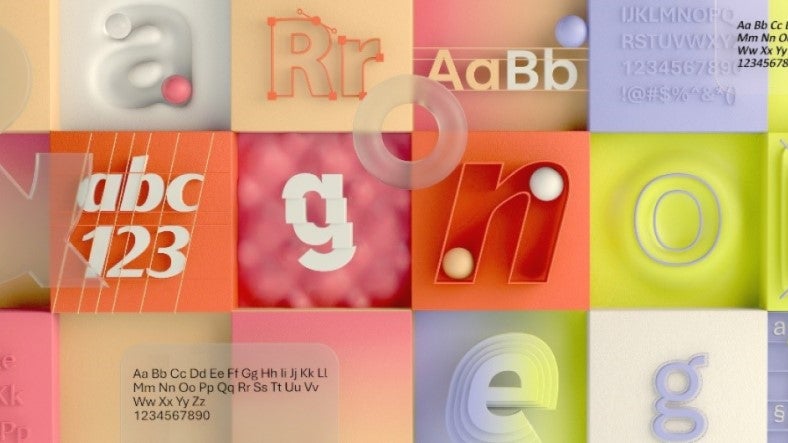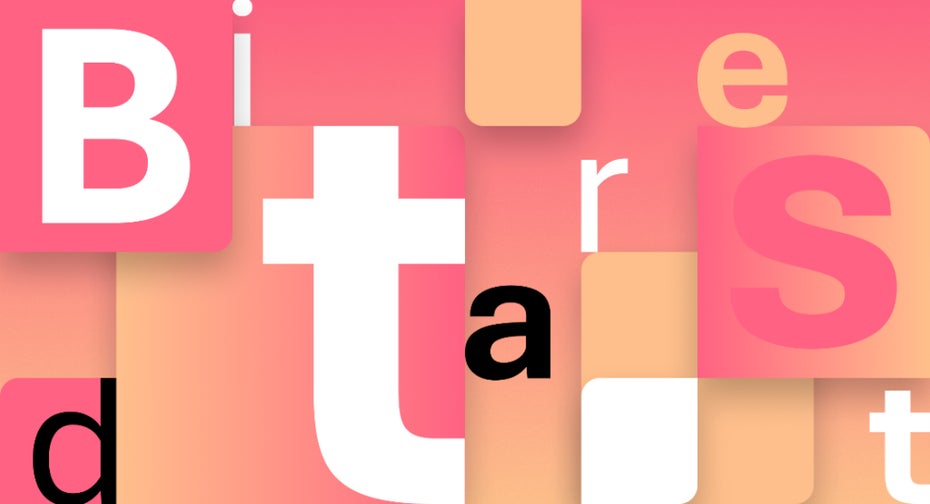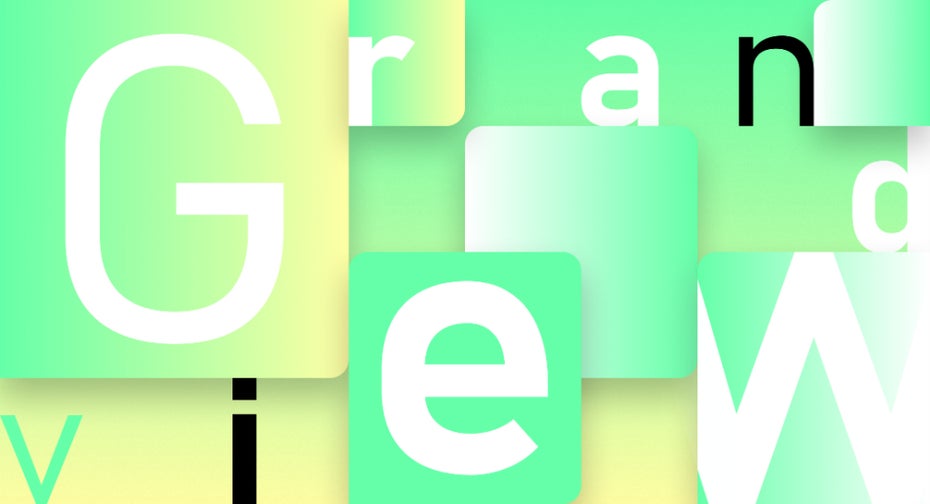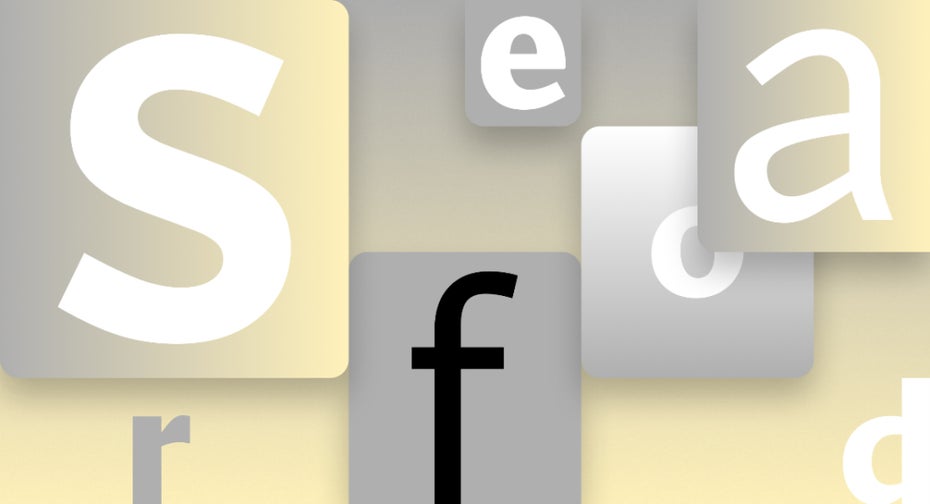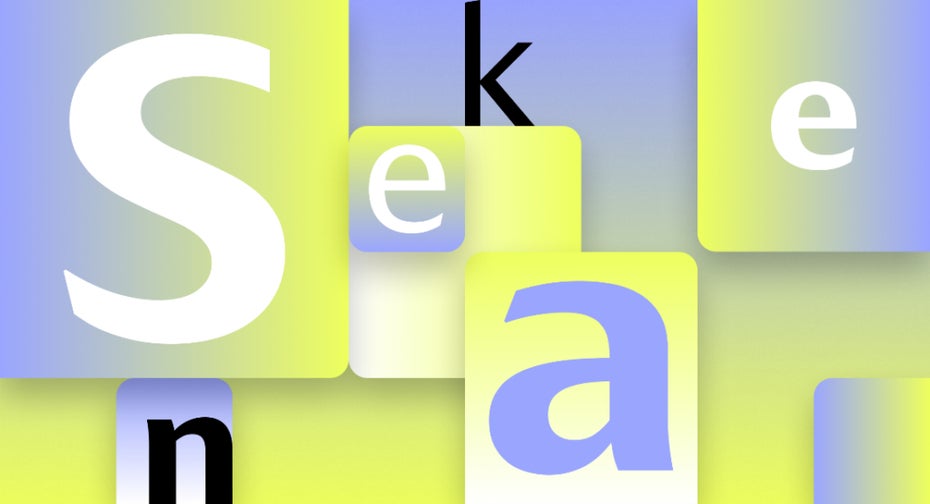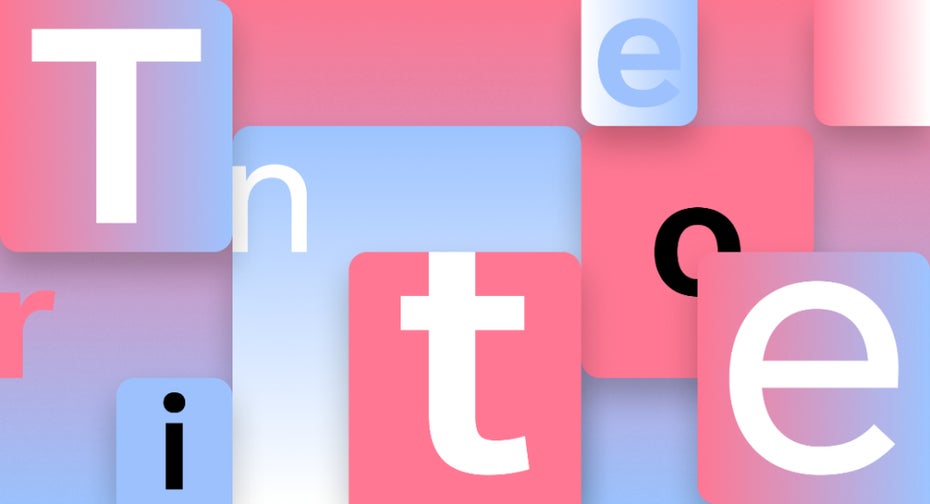
Tschüss Calibri: Das sind die Kandidaten für Microsofts neue Standardschriftart
Nach 15 Jahren ersetzt Microsoft Calibri und führt einen neuen Standard-Font ein. Einer der Vorschläge ist an deutsche Straßenschilder angelehnt.
Microsoft hat fünf neue Schriften designen lassen. (Grafik: Microsoft)
Seit 2007 ist Calibri die Standardschriftart bei Microsoft Office. Das soll sich jetzt ändern. Microsoft hat fünf Schriftarten vorgestellt, die als neuer Standard infrage kommen. Für die Entscheidung bittet Microsoft per Social Media um Feedback.
Alle Vorschläge sind serifenlose Schriftarten. Microsoft beschreibt sie als humanistisch, geometrisch, schweizerisch und industriell. Eine der Schriften ist außerdem von deutschen Verkehrsschildern inspiriert.
Unauffällig, aber aussagekräftig
Das Besondere an einer Standardschrift sei, dass sie vor allem unauffällig sein soll, um nicht von der Arbeit abzulenken, erklärt Microsoft. Gleichzeitig hätten sie einen großen Einfluss darauf, wie Dokumente oder E-Mails auf andere wirken.
Winzige Details könnten dabei eine große Wirkung haben. Der Abstand und die Formen zwischen den Buchstaben sei etwa genauso wichtig wie das Design der Buchstaben selbst.
Alle Fonts lassen sich schon jetzt über die Cloud ausprobieren. In einem Blogeintrag hat Microsoft die Designer und Designerinnen selbst erklären lassen, was ihr Schriftdesign ausmacht.
Das sind die Vorschläge:
Tenorite
Tenorite von Erin McLaughlin und Wei Huang. (Grafik: Microsoft)
„Nach Jahren mit Calibri – bekannt für weiche Ecken und enge Proportionen – sehnten wir uns nach etwas sehr Rundem, Breitem und Knackigem, und das geometrische Genre fühlte sich wie die richtige Richtung an“, erklären Erin McLaughin und Wei Huang die Idee hinter Tenorite.
Die serifenlose Schrift soll wärmer und freundlicher wirken als beispielsweise Times New Roman. Großzügige Zeichenabstände sorgen für mehr Ruhe und Offenheit. Große und runde Interpunktion soll für gute Lesbarkeit auch auf kleinen Bildschirmen sorgen.
Bierstadt
Bierstadt von Steve Matteson. (Grafik: Microsoft)
Bierstadt ist nach Angaben des Designers Steve Matteson von der Schweizer Typografie aus der Mitte des 20. Jahrhunderts inspiriert – präzise, schlicht, rational. Matteson assoziierte die Schweiz mit Bergen und benannte die Schrift deshalb nach einem der Gipfel von Colorado.
„Microsoft hat bereits die Arial – die viele Attribute von grotesken Schriften vor der Helvetica hat – und mein Ansatz war es, eine serifenlose Schrift zu entwerfen, die im Gegensatz zur Arial viel mechanischer und rationalisierter ist“, schreibt Matteson. Gleichzeitig sollen organische Akzente für mehr Menschlichkeit sorgen.
Skeena
Skeena von John Hudson und Paul Hanslow. (Grafik: Microsoft)
Auch Skeena basiert auf traditionellen serifenlosen Schriften. John Hudson und Paul Hanslow haben die Striche in dicke und dünnere Abschnitte aufgeteilt, sodass ein deutlicher Kontrast schwungvoll das Strichende markiert.
„Ich bin stolz darauf, dass Skeena respektvoll auf die Schriftformen des 20. Jahrhunderts anspielt und gleichzeitig einen Hauch von Ungewohntem hinzufügt“, erklätr Hanslow.
Seaford
Seaford von Tobias Frere-Jones, Nina Stössinger, und Fred Shallcrass. (Grafik: Microsoft)
Tobias Frere-Jones, Nina Stössinger und Fred Shallcrass haben Seaford entworfen und sich dabei an alten Serifenschriften orientiert. „Wir hofften, die gleiche, vertraute Art von Wärme zu erzeugen, aber ohne die Serifen“, erklärt Tobias Frere-Jones.
Sanft organische und asymmetrische Formen sollen Unterschiede zwischen den Buchstaben betonen und so das Lesen erleichtern.
Grandview
Grandview von Aaron Bell. (Grafik: Microsoft)
Aaron Bell hat sich beim Design von Grandview an klassischen deutschen Straßen- und Eisenbahnbeschilderung orientiert. Stichwort: Gute Lesbarkeit aus weiter Entfernung, auch unter schlechten Bedingungen.
Die Höhe der Buchstaben soll auch am Bildschirm gute Lesbarkeit garantieren. Um das Schriftbild an Fließtext anzupassen, hat Bell die Breite leicht verlängert. „Das daraus resultierende Design bewahrt die Stimme des Originals und eignet sich hervorragend für lange Texteinstellungen“, beschreibt Bell das Ergebnis.